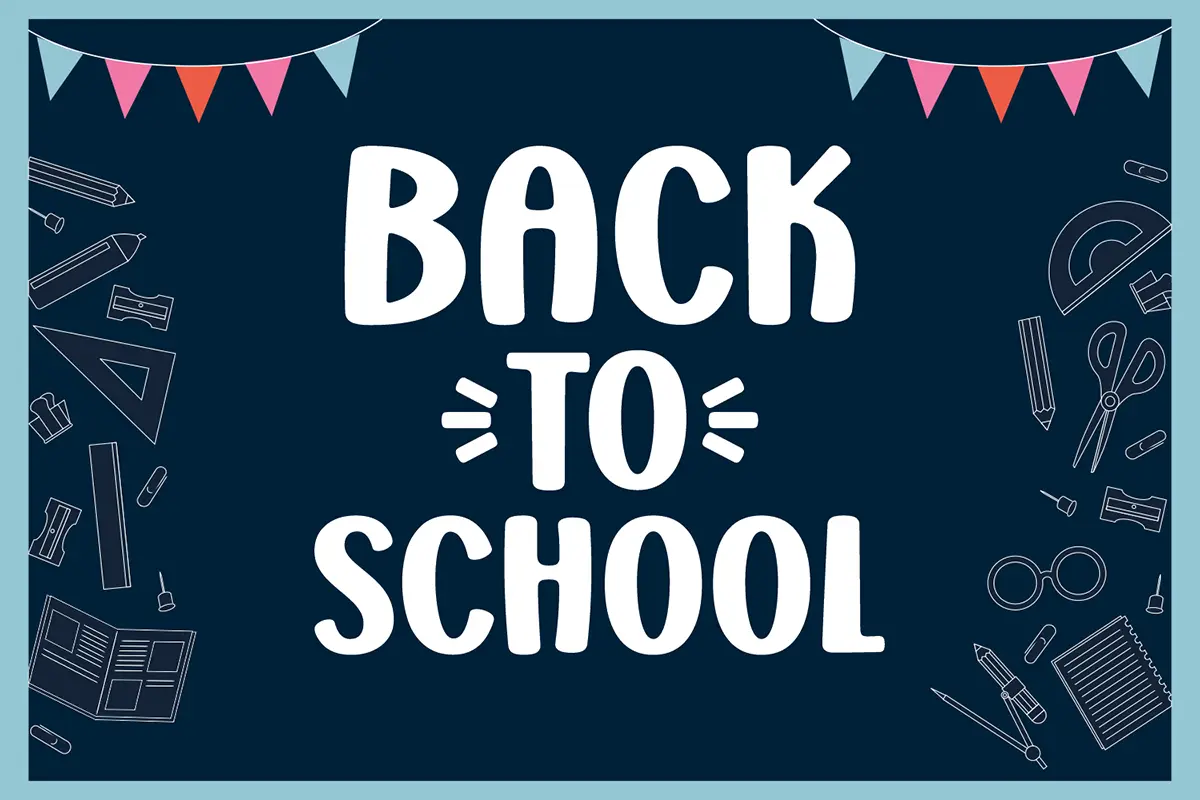
فونت نمایشی Holla Weekend
Holla Weekend یک فونت نمایشی با حروف ضخیم، دوستانه و پرانرژی است که حس شادابی و بازیگوشی را در طراحیهای شما ایجاد میکند. این فونت انتخابی عالی برای پروژههای کودکان، فعالیتهای آموزشی و طراحیهای سرگرمکننده است.
💡 ویژگیها
- حروف ضخیم و خوانا با استایل سرگرمکننده
- الهامگرفته از حال و هوای آخر هفتههای شاد و غیررسمی
- مناسب برای استفاده در پوسترهای کودکانه، بروشورهای آموزشی و پروژههای چاپی و دیجیتال
- حس واقعی و صمیمانه برای برقراری ارتباط بهتر با مخاطب کودک